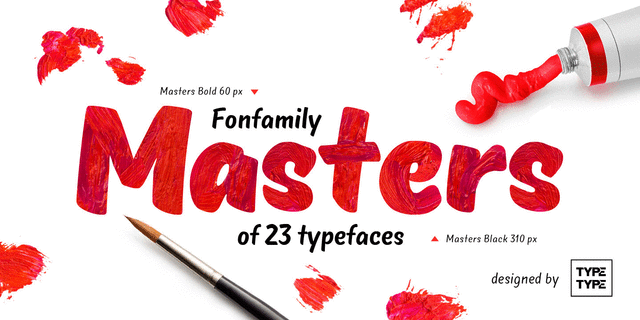
Мастерс – это очень эмоциональная гарнитура. Начертания этого семейства добавят искренности и повысят доверие к вашему продукту. Шрифт содержит четыре стилистических набора: Masters (основной), Masters Birds (птицы), Masters Rough (грубый) и Masters Condensed (компактный). Каждый набор представлен в пяти классических весах: Тонкий, Светлый, Нормальный, Жирный и Сверхжирный. Мастерс предназначен для использования в логотипах, заголовках и другой акциденции рекламного или развлекательного характера. Шрифт разработан Иваном Гладких в студии TypeType в 2015 году.
живой, динамичный, свежий, холодный, худой, легкий, тонкий, чистый, весенний, невесомый, прозрачный, проволочный, аккуратный, простой, дружелюбный, доверительный, доброжелательный, приветливый, добрый, рукотворный, натуральный, органический, природный, мягкий, ремесленный, здоровый, позитивный, понятный, доступный, крафтовый, артизанальный, растительный, вкусный, мультяшный, радостный, честный, гладкий, сочный, праздничный, домашний, счастливый, милый, симпатичный, забавный, прикольный, игривый, лихой, зеленый, ручной, тяжелый, толстый, тесный, сильный, заметный, броский, детский, черный, смелый, яркий, активный, свободный, стройный, практичный, экономичный, кустарный, самодельный, экологичный, фермерский, птичий, смешной, остроумный, задорный, озорной, подвижный, оригинальный, наивный, летний, осенний, неряшливый, непоседливый, вернакулярный, колючий, острый, грубый, рваный, бытовой, винтажный, трудолюбивый, теплый, ламповый, добротный, громкий